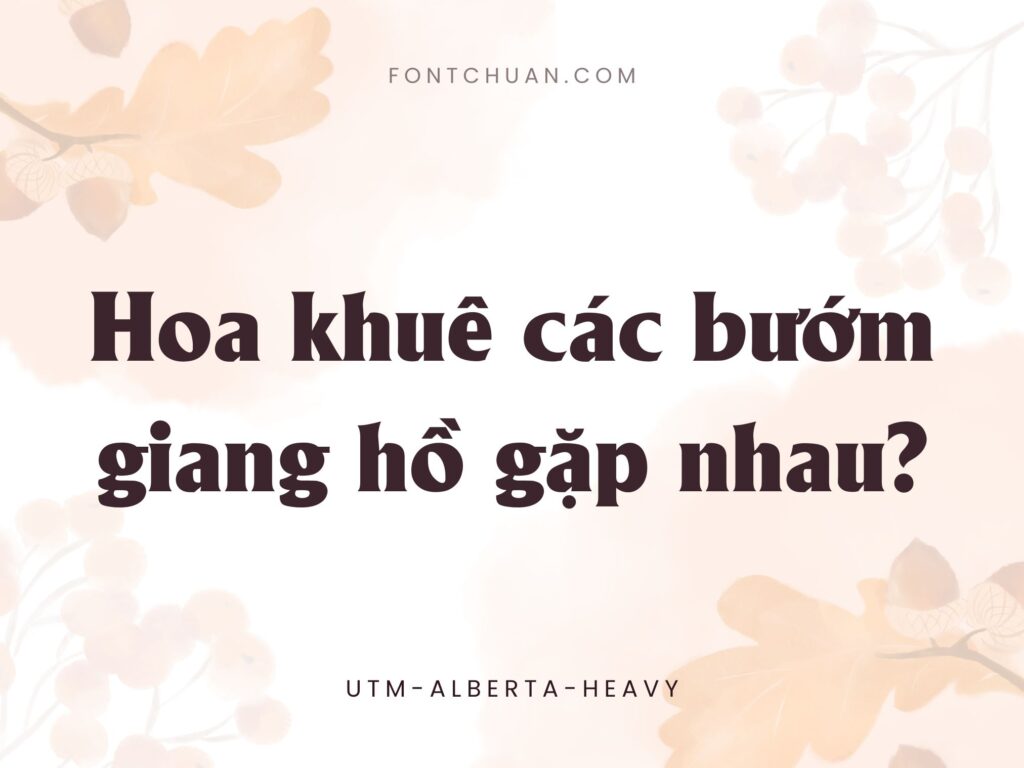
Font UTM Alberta Heavy Việt Hóa
UTM Alberta Heavy là một kiểu Font Serif đậm, mang phong cách cổ điển và mạnh mẽ. Font này thường được xếp vào nhóm Font Slab Serif nhờ vào các đường nét dày, vuông vức và chắc chắn, giúp tạo ấn tượng mạnh mẽ trong thiết kế. Ngoài ra, để cân bằng sự cứng cáp, nhiều nhà thiết kế còn kết hợp UTM Alberta Heavy với các Font chữ viết tay hay Font Script mềm mại nhằm tạo sự hài hòa giữa mạnh mẽ và uyển chuyển. Font này hỗ trợ đầy đủ tiếng Việt cùng hơn 100 ngôn ngữ khác. Thành viên của Font Chuẩn đã sưu tầm và chọn lọc font này nhằm đáp ứng nhu cầu đa dạng của bạn đọc và ứng dụng thực tế vào các dự án thiết kế.
UTM Alberta Heavy có cấu trúc chữ với các nét dày và chắc chắn, tạo nên vẻ đẹp mạnh mẽ và dễ đọc. Font này phù hợp cho các ứng dụng như thiết kế tiêu đề, poster, logo và bao bì sản phẩm. Các ngành nghề như quảng cáo, bất động sản, giáo dục và công nghệ có thể tận dụng UTM Alberta Heavy để tạo điểm nhấn độc đáo trong thiết kế.
Tác giả: Geoffrey Lee